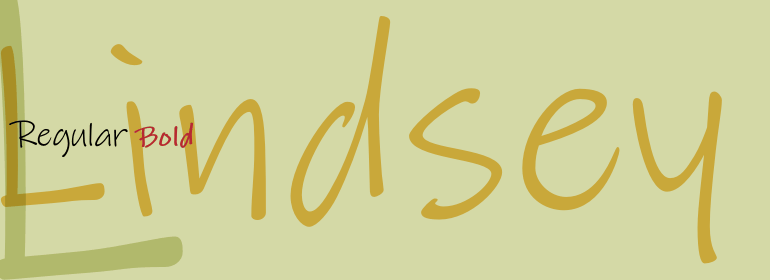
Lindsey
Lindsey,这款字体结构工整、笔画清晰,兼顾美观与易读性,适用于标题、正文、海报、包装、LOGO 等多种场景。字形优雅稳定,风格百搭耐看,适配日常排版与创意设计,让文字呈现更舒适、更具质感。Lindsey一笔一画,皆是细节,以均衡的比例、流畅的线条打造舒适视觉体验,字形端正大气,风格简约现代。无论是商业设计、品牌宣传还是日常排版,都能轻松驾驭,让文字更有格调与力量。Lindsey字体下载。
字体品牌: Ascender(Monotype) 设计师:Matteson,Steve 字体分类:衬线体 字体属性:外文 字符集:Unicode 发布时间: 2018